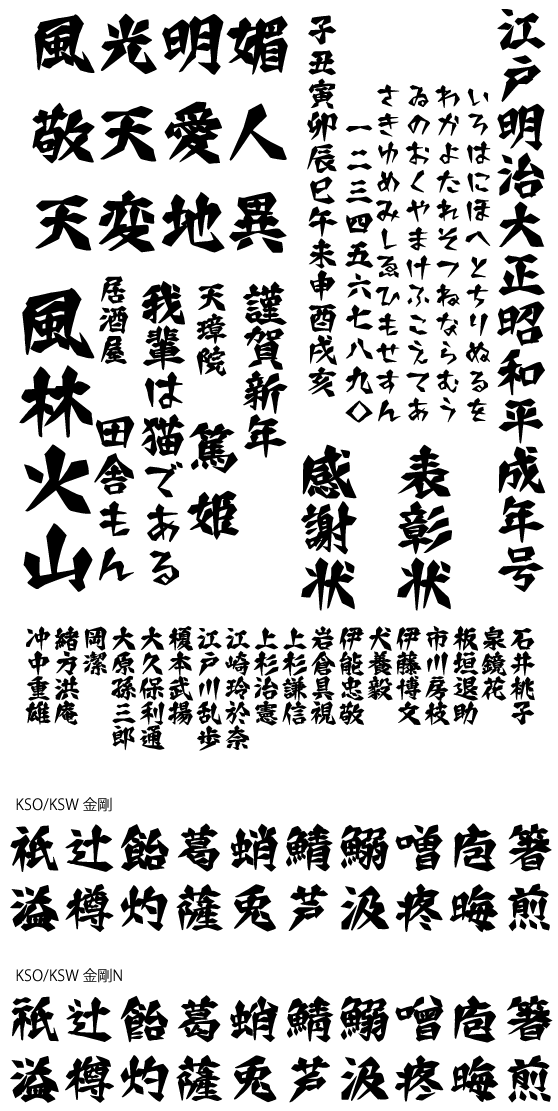
デザイン毛筆
金剛書体 (KSW金剛・~N同梱)
遊び心の入った昭和デザイン書体シリーズ第3弾です。「金剛⇒ダイアモンド⇒硬い」をイメージして仕上げました。インパクト抜群の書体です。
昭和書体は、あらゆる使用目的にマッチする毛筆書体の提供を目指し、揮毫職人が1文字1文字丁寧に書き上げた本格毛筆書体ブランドです。